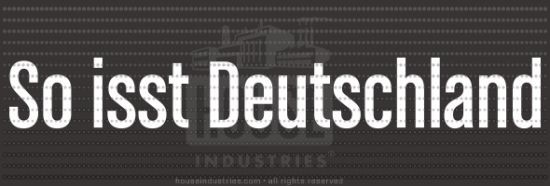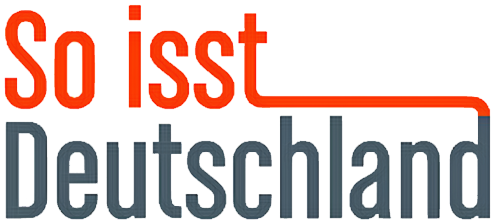
so isst deutschland
ich suche die schrift aus dem logo der kabel-eins-sendung »so isst deutschland«:
erst dachte ich »pah, die kennst du doch!«, aber keine hat genau gepasst, vor allem beim »t«, »c« und »a«. es ist nicht:
alternate gothic
bureau grotesque
ff din oder din 1451
grotesque mt
helvetica
news gothic
aber welche ist es denn? schon mal danke :D
Könnte es vielleicht eine gestauchte Folio condensed sein?
Der Schriftzug sieht ein wenig gequetscht aus;
Ich bin aber auch noch am rätseln.
edit: mein erster Gedanke war eigentlich Helvetica Inserat, aber die ist fetter.
... hm, Univers (Ultra) Condensed auch nicht, dabei war ich mir fast sicher ...
Chalet Comprimé Cologne 1960?
Ein bißchen zu fett, aber ziemlich nah dran.
näher als alle anderen vorschläge. vielen dank! :)